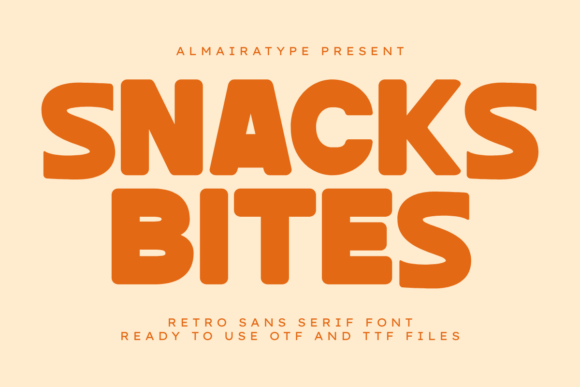
Snacks Bites
適切なデザイン要素を見つけるのは難しい場合がありますが、Snacks Bitesは作品を即座に引き立てる優れたコレクションを提供します。
POD(オンデマンド印刷)製品、結婚式の招待状、またはソーシャルメディアのグラフィックを作成している場合でも、Snacks Bitesは理想的です。